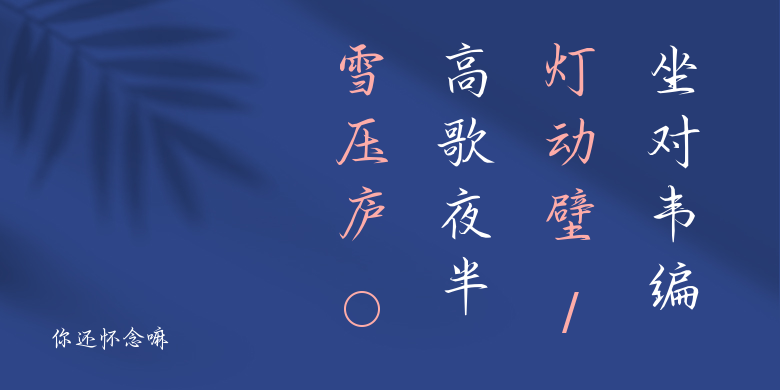
你还怀念嘛
你还怀念嘛,这款字体结构工整、笔画清晰,兼顾美观与易读性,适用于标题、正文、海报、包装、LOGO 等多种场景。字形优雅稳定,风格百搭耐看,适配日常排版与创意设计,让文字呈现更舒适、更具质感。你还怀念嘛一笔一画,皆是细节,以均衡的比例、流畅的线条打造舒适视觉体验,字形端正大气,风格简约现代。无论是商业设计、品牌宣传还是日常排版,都能轻松驾驭,让文字更有格调与力量。你还怀念嘛字体下载。